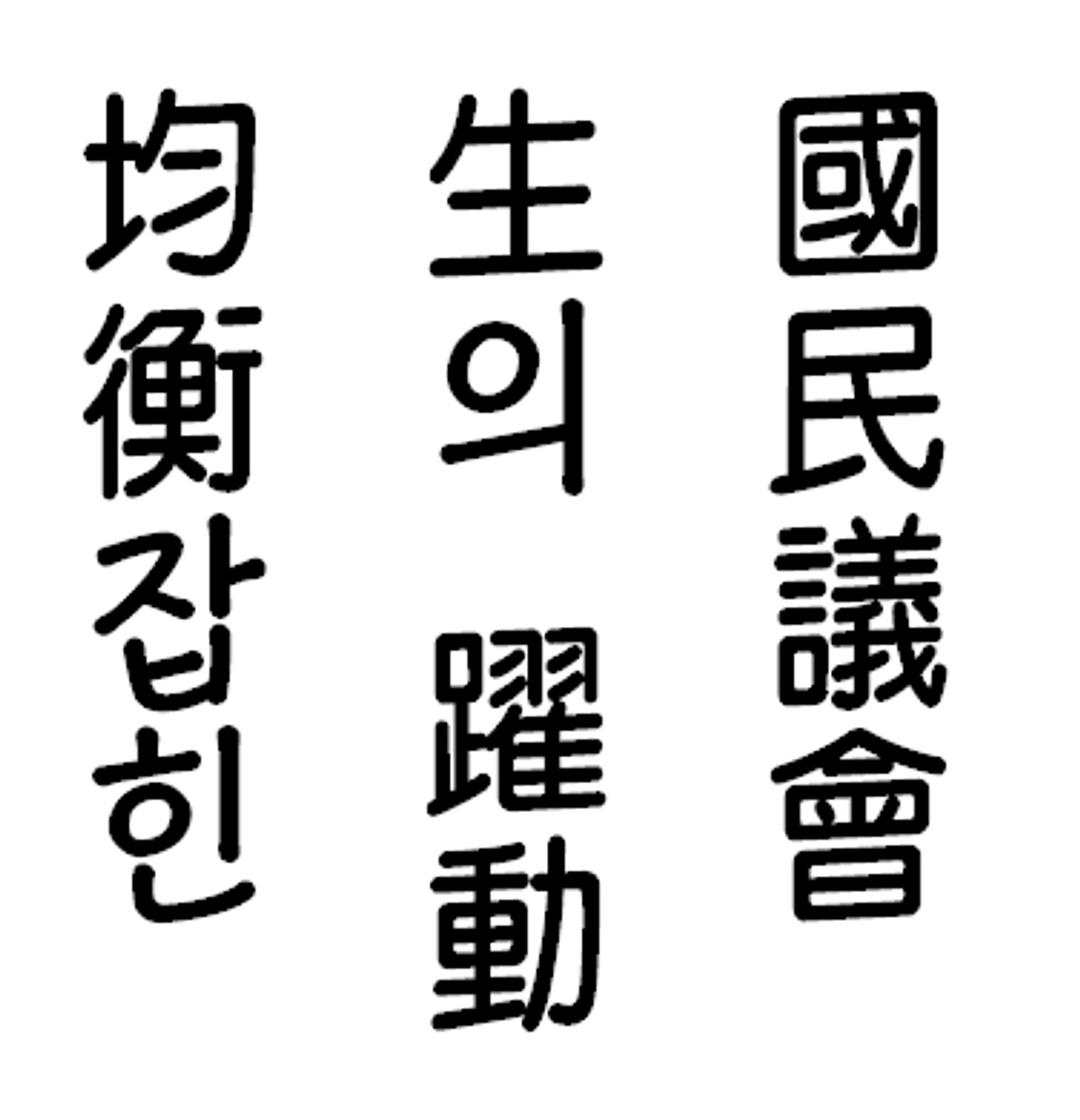
3-STEP CAMPUS PROJECT의 폰트명 알려주세요~ 유료폰트명이면 비슷한 무료폰트명도 알려주시면 감사하겠습니다! 오늘중 최대한 빨리 알려주시면 답변 채택하겠습니다.
실제 폰트가 아닙니다
오른쪽 텍스트를 보니 전형적인 ChatGPT 생성 글씨체와 매우 유사했고, 또 외국 폰트 검색 사이트에서 검색해 보았으나 완벽히 일치하는 폰트가 없어 실제 폰트는 아닌 것 같다라고 생각됩니다. 비슷한 폰트로는 QB One 시리즈 추천드립니다